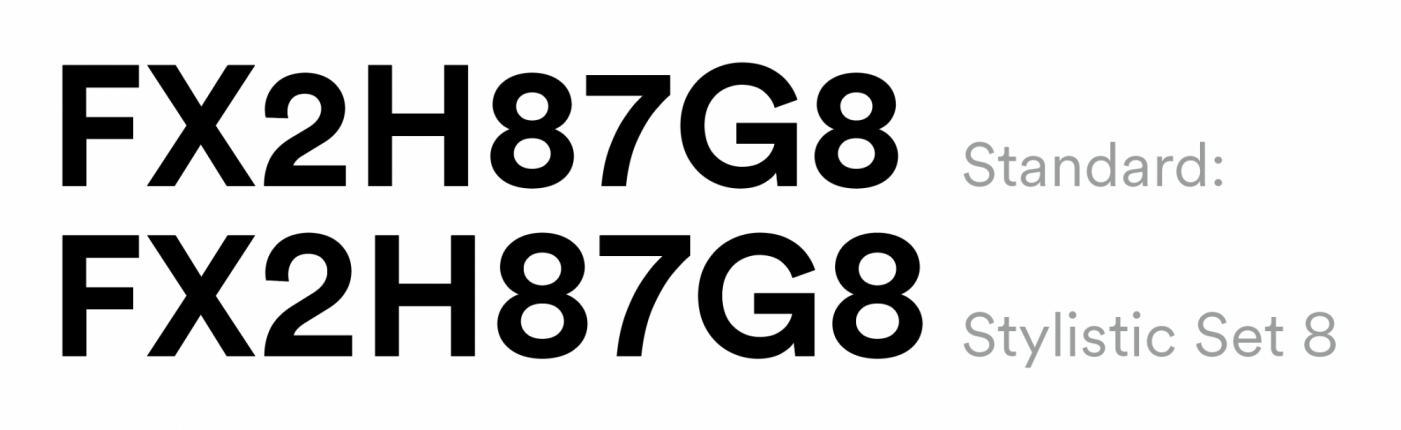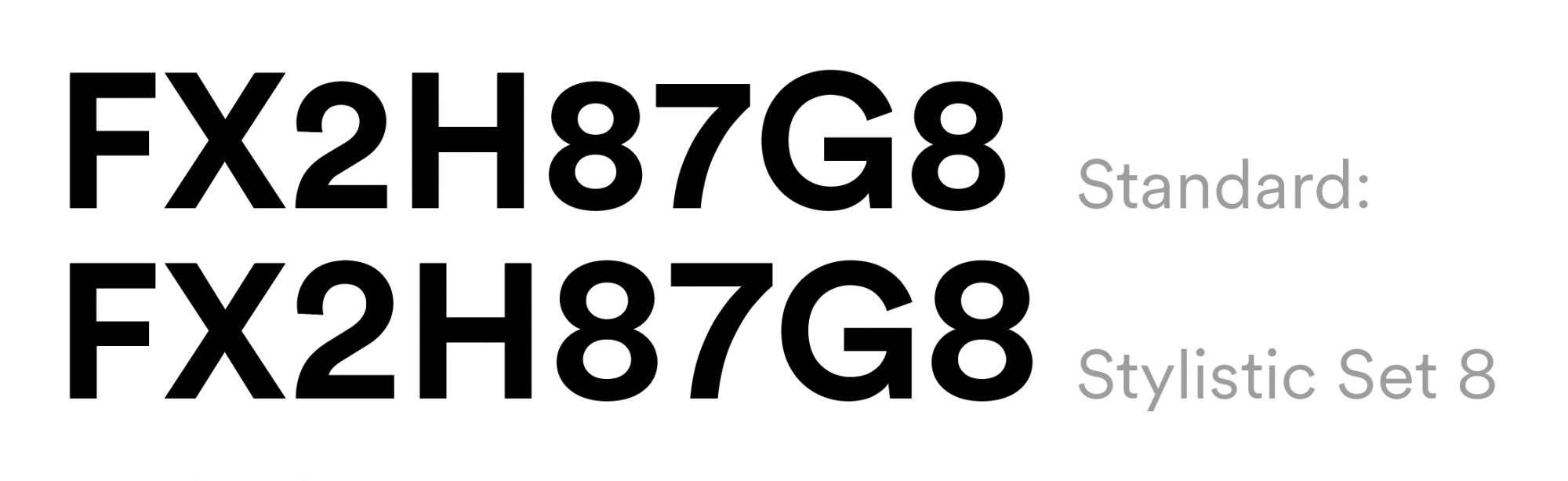
… und wieso ich vorher schrieb, dass der Preis halbwegs gerechtfertigt ist, ist dass die Schriften stilistisch top sind. Viele Alternativen haben halt nicht das gewisse etwas – eine Akkurat ist eben eine Akkurat … Replica, Simple … alles Klassiker. Wird auch seinen Grund haben, wieso sich Microboy die Circular zugelegt hat.
Die Schriften wird man auch in einigen Jahren noch einsetzen können, ohne dass man der Arbeit nen Zeitstempel aufdrückt.
Was mich extrem an der Circular nervt sind die Ziffern. Diese sind leider auf die Verwendung im Fließtext optimiert und somit etwas niedriger als die Versalien. Im Versalsatz sieht das natürlich extrem putzig aus und man kommt nicht drumherum die Ziffern etwas zu verzerren ... Ein Ziffernsatz passend zu den Versalien wäre ja eigentlich keine große Sache.
Lineto hat meine Wünsche erhört und der Circular Ziffern in Versalhöhe spendiert!
Gerade zufällig beim testen der OpenType-Features bemerkt!
irgendwie auch gut
Erinnert mich irgendwie an die Antique Olive, so retro-zeitgeist-mäßig … aber kann man sich nicht trauen, oder?
Da fallen mir spontan diese ein:
In die Reihe passt indirekt auch die Patron
vor 2 Stunden schrieb Microboy:
In die Reihe passt indirekt auch die Patron
Wenn ich die Patron sehe, lande ich unweigerlich bei der Gräbenbach. Aber das führt dann zu weit weg von der Circular.
vor 20 Stunden schrieb Microboy:
Und wieder einmal bin ich auf der Suche nach einer Alternative zur Circular ... :rockon:
Ganz anderer Style aber irgendwie auch gut:
Das sind ja streng genommen schon mal drei neue Stränge für sich. 😬😉
An der Subtil ist die National 2 ziemlich nah dran, hat 3 Weiten mehr aber – auch nach beharrlichem Knietschen meinerseits – leider kein ẞ. Mittlerweile scheinen sie sich aber auch besonnen zu haben bei ihren neueren Sachen. 😐
Außerdem – weil in drei Geschmacksrichtungen:
Dazu hier noch leicht verhipstert und gerade günstig zu haben: